永久免费素材!阿里全套 6 款免费中文设计字体合集打包下载 (正版可商用)
最近阿里发布了三款全新「免费中文字体」,分别是阿里妈妈方圆体、阿里妈妈灵动体和阿里妈妈刀隶体。跟之前的「阿里巴巴普惠体」一样,这些字体完全免费,并且可用于商业用途。
加上早前发布的钉钉进步体、阿里妈妈东方大楷、阿里妈妈数黑体等,一共 6 款字体永久免费!我们提供了打包下载,这些正版免费素材无论对职业设计师,还是普通个人办公用户来说,都是不可多得的好资源,毕竟一套正版字体授权非常昂贵,阿里在这点上算是极其厚道了!
不可多得的「免费可商用的中文字体」素材
过去由于中文字体制作成本很高,相应的版权费用也非常高昂。对于中小企业、小商家、个人用户等都很难负担。而随着阿里领头,发布颇具“普惠”意义的「阿里巴巴普惠体」之后,越来越多免费字体如小米 MiSans、荣耀字体、鸿蒙字体、OPPO Sans、金山字体等涌现了出来。
为了进一步能为企业、个人的商业营销提供更多免费的字体,阿里旗下的阿里妈妈也发起了一个叫做「智造字」的项目。这个项目目标是通过人工智能 AI、机器学习技术以及可变设计的能力,持续地为用户提供更多优质、精美的可商用的免费字体,为商业和设计降低成本而努力。
下面,我们一起来看看阿里妈妈·智造字所发布的一些精美的免费中文和英文字体的实际效果吧。后面我们也提供了打包下载,方便大家下载收集全套的阿里免费字体。无论用来平面设计、Logo、宣传海报,还是网页、APP、文档使用都非常实用。
阿里妈妈方圆体
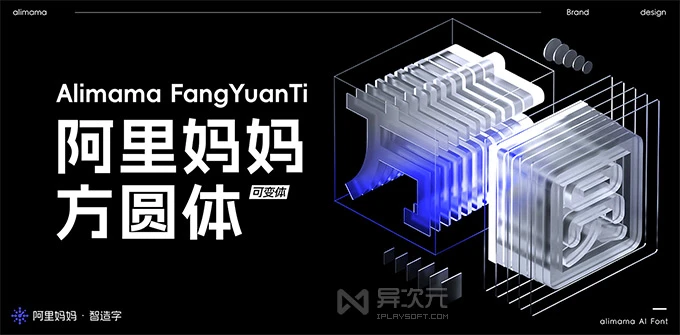
「阿里妈妈方圆体」(AlimamaFangYuanTiVF) 是“阿里妈妈·智造字”通过人工智能 AI 方式打造出来的一款超酷的免费中文字体。它是一种简体中文的双轴可变字体,集合了各种中文字符,包括但不限于 GB2312 标准里的 6763 个汉字,还有 52 个英文字母(大小写都有),以及 227 个常用标点符号,总共高达 7042 个字符。
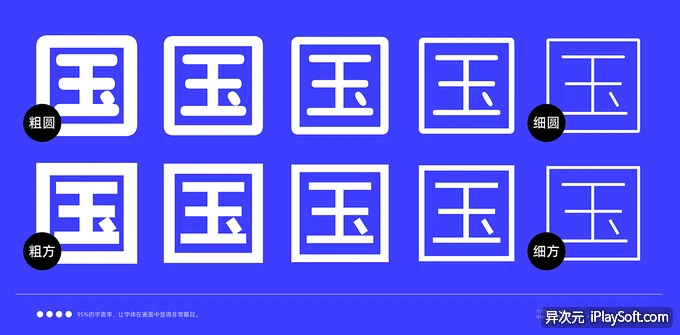
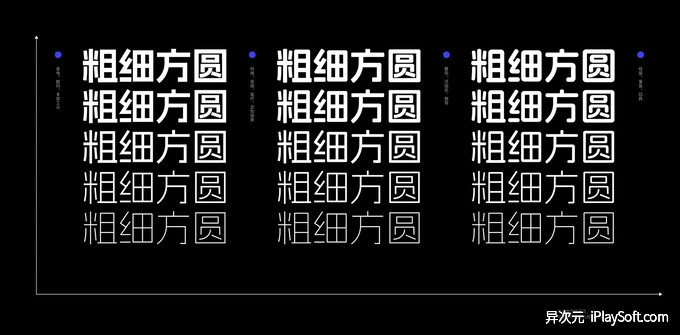
据介绍,阿里妈妈方圆体这套字体是通过 AI 在 20 天内生成完成的,是国内外少有的中文“双轴可变字体”。方体看起来坚实而有力,圆体则显得润泽而柔美。这两种风格的切换让字体显得刚柔并济,实用性极高,同时也为创意设计提供了更多的可能性。
阿里妈妈方圆体实际使用效果图:
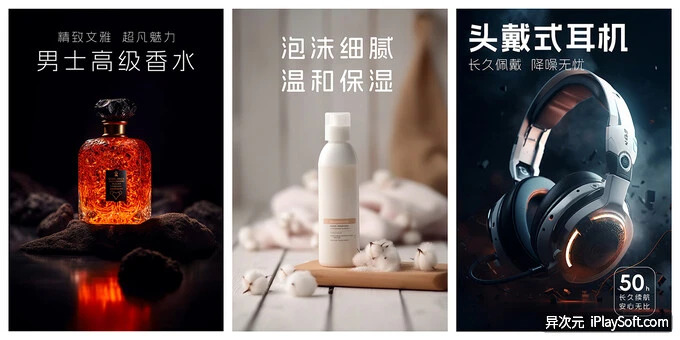
而且,阿里妈妈方圆体字体的粗细还可以随意调整,设计师们可以进行无限微调,使得创意设计拥有更加丰富多样的表达。
阿里妈妈灵动体 (英文字体)
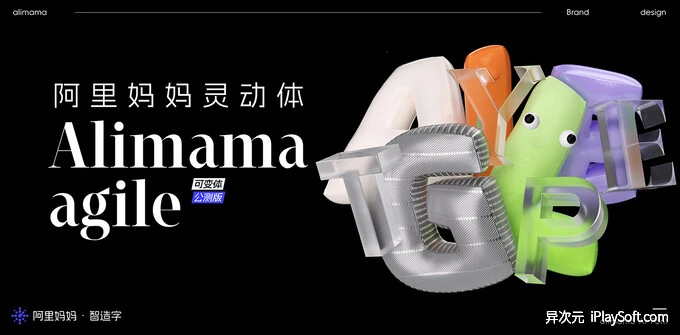
「阿里妈妈灵动体」(Alimama Agile),是一款超酷的英文 (西文) 字体。它不仅可以变粗、变宽、倾斜,还可以加上衬线,总共有四种字体变化方式。而且,这款字体包含了大小写英文字母共计 52 个,还有 68 个常见标点符号,一共拥有 120 个字符。
阿里妈妈灵动体是一款四轴可变的西文字体,它可以根据需要进行四个方面的变化:字重、字宽、倾斜和衬线,拥有非常广阔的使用场景!
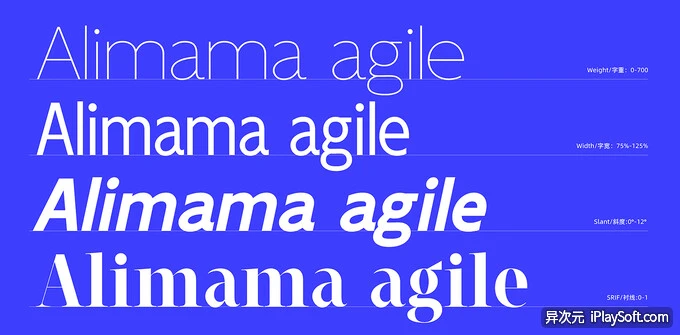
通过调整字重,可在版式中灵活地调整信息的层次结构,并对各种落地物料进行微妙的优化。字宽的可变性使得信息的排列更加灵活,可以更好地适应整体画面。
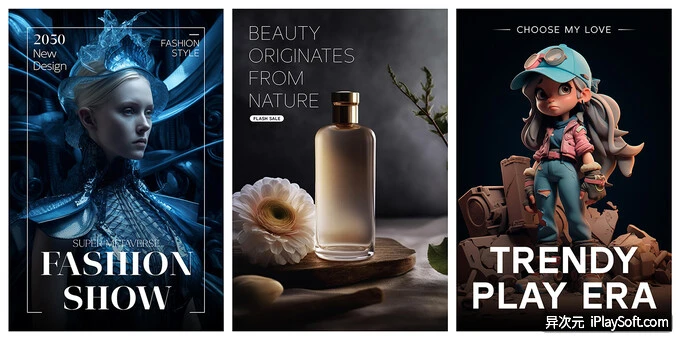
倾斜效果的可变性使得字体具有突出强调的特点,增加了文本的美感和艺术性。而衬线的可变性则使得字体可以从无衬线字变为衬线字,满足了不同用户的需求,涵盖了西文的两个主要类别。
阿里妈妈刀隶体
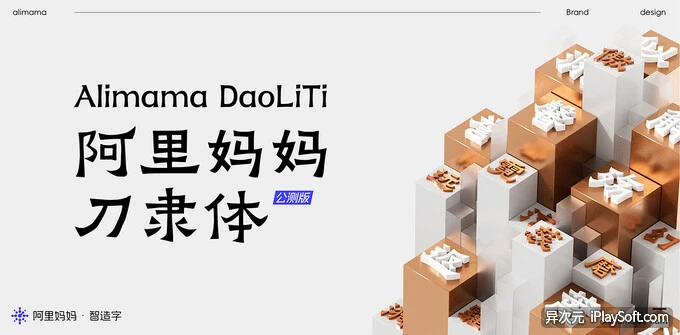
「阿里妈妈刀隶体」(AlimamaDaoLiTi) 是阿里巴巴推出的一款中文简体字库,目前仅有一种字重。它收录的中文字符包括但不限于 GB2312 标准中的汉字,总共有 6763 个。
此外,还包括了大小写共 52 个英文字母和 227 个常用标点符号,总计达到 7042 个字符。可以说,这个字库非常全面,能够满足各种文本的需求哦。
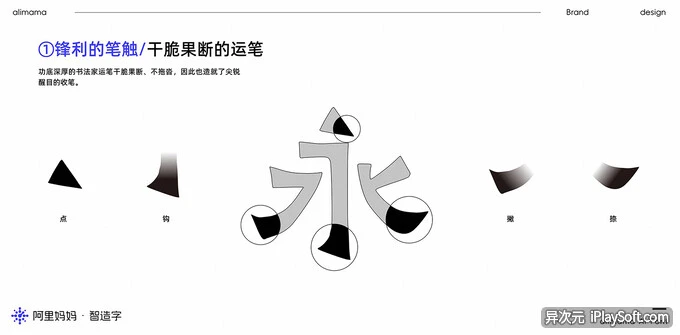
阿里妈妈刀隶体通过机器学习,吸收了爨宝子碑的精华,强调了三角点折弯和横画两端的“雁尾”形状,给人一种锋芒毕露的感觉,展现出其精神特质。
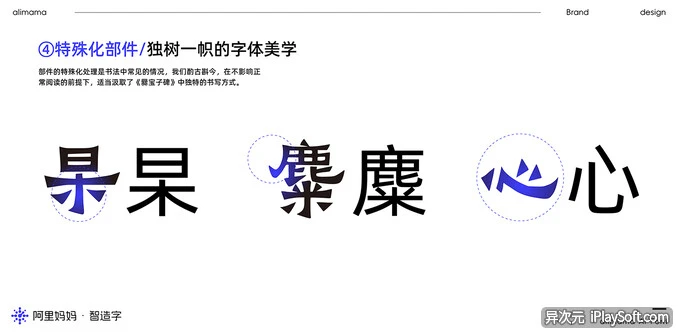
这种字体介于隶书和楷书之间,保留着浓厚的隶书方笔风格,给人一种坚实、朴实、稚拙而又倔犟的感觉。
阿里妈妈刀隶体效果图:
它打破了常规的匀称均衡,每个字的大小常常出人意料,看似不按常理出牌,实则在艺术上深得其道理,故意在不规则中追求整体的和谐。它活静中蕴含着动感,动感中又寓含着静谧。
阿里妈妈数黑体
「阿里妈妈数黑体」(AlimamaShuHeiTi) 就是一款很有设计感的漂亮中文字体,只有粗体一种字重,相对较为适合用来设计标题、制作海报等作品。
这款字体收录了 GB2312 显示简体中文字形,总共有 7025 字符,其中包括 6767 个全角汉字,还有大小写英文字母 52 个,以及常用的标点符号共 206 个。
阿里妈妈数黑体字体看起来饱满有力,姿态挺拔,排版简洁现代。每个字都透露着前卫、时尚的视觉感受,给人一种先锋的氛围。它非常适用于电商、广告、品牌形象和推广物料等各种场合。
阿里妈妈数黑体使用效果演示:
阿里妈妈东方大楷
「阿里妈妈的东方大楷」(AlimamaDongFangDaKai) 是一款“很醒目”的简体中文字库,只有一种字重,包含了 GB2312 标准下的汉字,总共有 6763 个。还有大小写的英文字母、半角全角以及一些特殊的合体字等,一共有 105 个。
另外,还有常用的标点符号,总共有 175 个。整个字库里合计共有 7043 个字符可以使用。而且最棒的是,它是永久免费商用的哦!
阿里妈妈东方大楷字体利用了颜真卿的多宝塔碑算法进行生成,并结合了人力的辅助完成。这套字库通过机器学习,成功地捕捉到了颜体字的丰满而厚重的感觉。在描摹笔画的过程中,它还能够准确地展现传统书法中的起伏和变化。
它规范了字形的骨架和笔画,还还原了书法中的一些技巧,比如落笔、转笔、藏锋、护尾等,使得整体的字体更加丰满、圆润、厚实。
钉钉进步体
「钉钉进步体」(DingTalkJinBuTi) 是一款超赞的标题艺术设计中文字体,完全符合 GB2312 规格。它包含了汉字 6763 个,还有 150 个拉丁字母和拉丁扩展字符,以及 613 个标点和其他字符,总共达到了 7526 个字符。
这款字体以 7° 的斜体角度设计,既展现了科技感又兼具书写的美感。它非常适合在线上、线下广告宣传、多渠道营销和空间导视等各种场景中使用。这款字体是专为标题设计、LOGO 设计的艺术字体,而且对于个人和组织来说是完全开放的——永久免费商用!